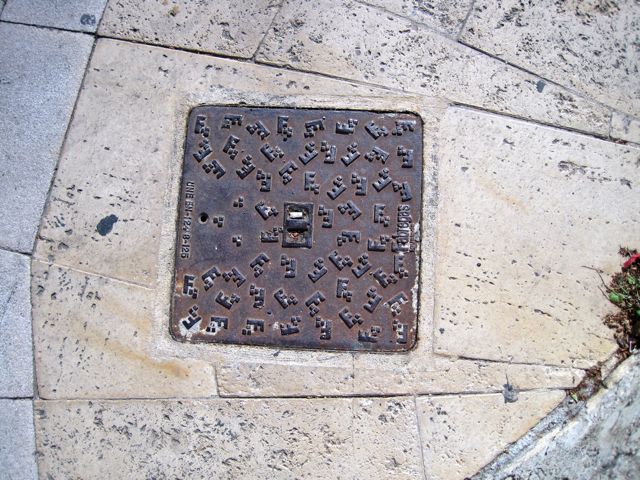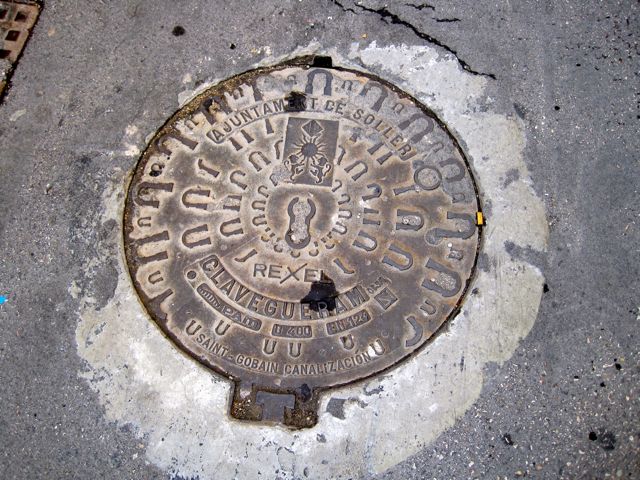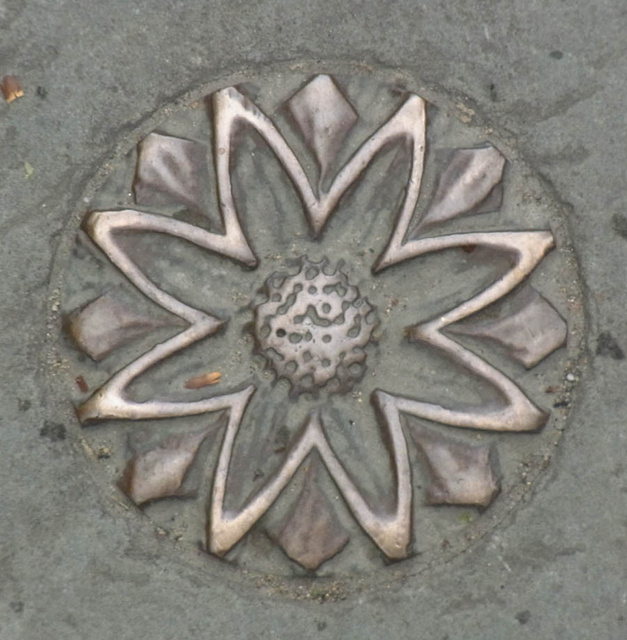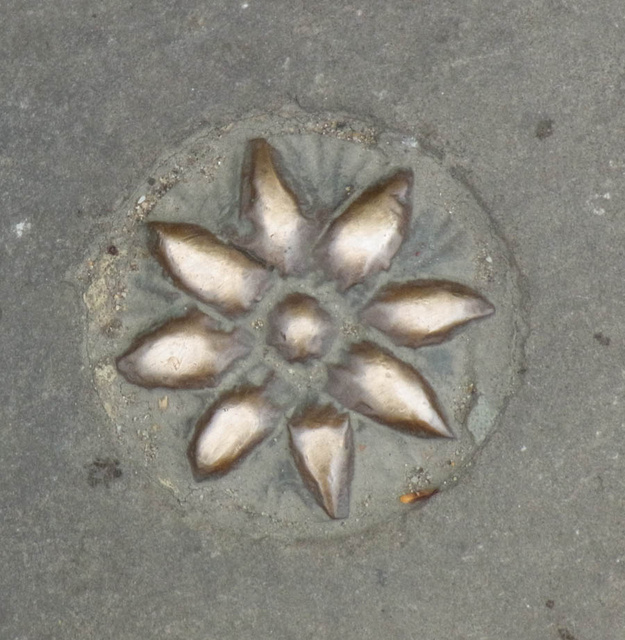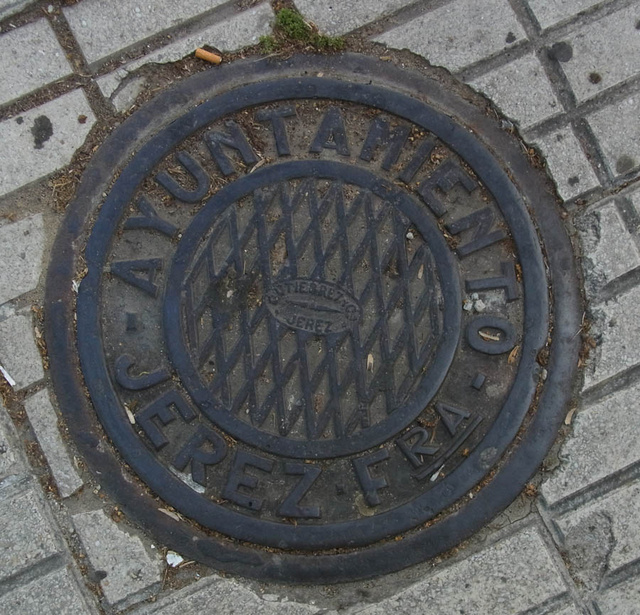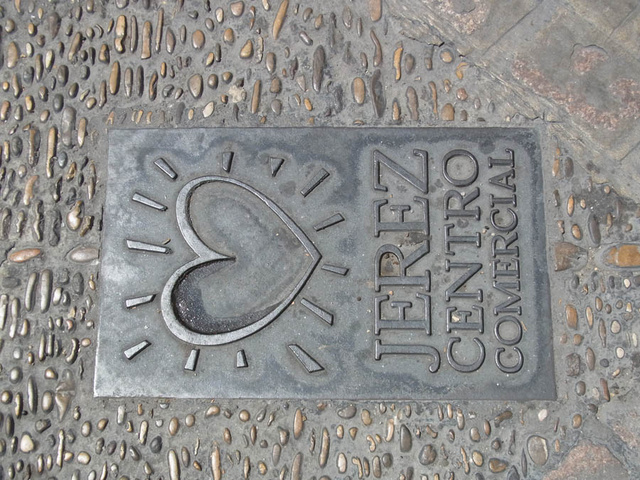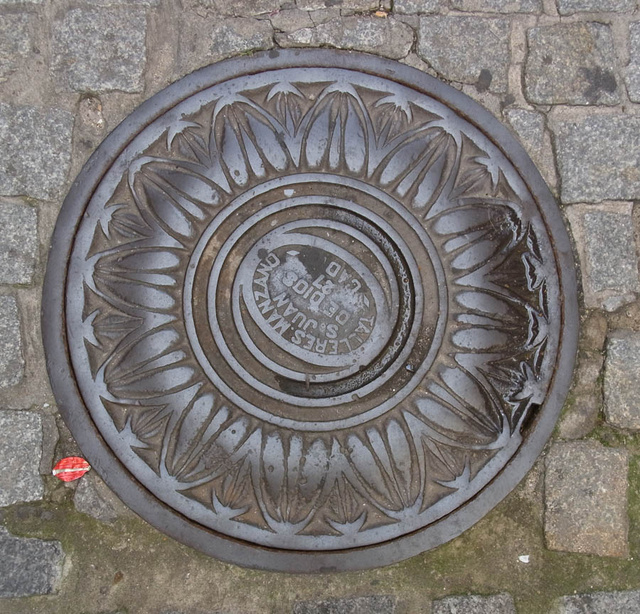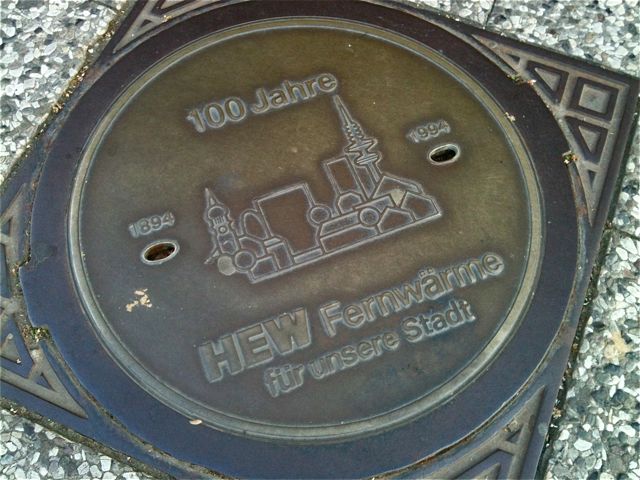
Sagt mal, kann irgendeiner der anwesenden Schriftkundigen diesen Buchstabensalat deuten?
Heißt das WYLK, YWLK, oder ist steckt da nicht sogar noch ein A drin? Das Teil liegt auf den Philippinen, wahrscheinlich in Manila und der Salat könnte auf eine Gießerei oder einen Wasser- oder Stromversorger deuten, vielleicht auch ein Telekommunikationsunternehmen — was sich halt alles so unter Schachtabdeckungen tummelt.
Ist es einfach Schrift?
Ganz ähnliche Zeichen:
Freund bertel vermutet, glaube ich, dass es sich um ein Schriftzeichen handelt. Ein handelsübliches sozusagen, woraus sich die erstaunliche Ähnlichkeit ergeben würde. Bliebe bloß die Frage, welches Land solche Zeichen schreibt oder früher schrieb. :-?
Freund bertel vermutet, glaube ich, dass es sich um ein Schriftzeichen handelt.
Auch bertel sieht eine Ligatur (oder ist das dann eher ein Monogramm? Jedenfalls abstrahierte Buchstaben übereinanderliegend) in seinem Beispiel, denn M A L und I sind doch erkennbar.
Nach einer oberflächlichen Suche behaupte ich dennoch, dass es sich bei der Deckelprägung um lateinische Zeichen handelt.
Keine echten manhole covers und daher vermutlich nur von untergeordneter Bedeutung, aber diese Ornamente findet man im Englischen Cambridge überall auf den Gehsteigen:
Hübsch! Ob das wohl reine Dekoration ist? Oder handelt es sich um schön gestaltete Messpunkte oder Markierungen?
Wohl kaum, dafür sind es viel zu viele die sich überall in der Stadt befinden. Ich glaube es handelt sich wirklich um Verzierungen.
Um wenigstens noch etwas Material nachzuliefern: hier sind zwei echte manhole covers sowie eine Verzierung vom Spanischen Jerez de la frontera. :-)
Eschwege:
Hamburg:
In der Nähe des hübschen Englischen Hafenstädtchens Mevagissey in Cornwall finden sich die »Verlorenen Gärten von Heligan«. Hier werden wunderschöne und soweit ich herausfinden konnte wohl zumindest zum Teil auch originale Eisengitter als manhole covers verwendet.
Wobei man sich ja schon fragen muss, wo man landet, wenn man in Venedig in einen Gulli steigt … :-o
Mal wieder ein paar iPhone-Details aus Chur, Graubünden, Schweiz.
Ich hatte ja auch noch einen Gullideckel angekündigt.
Ich habe hier noch was hauptstädtisches gefunden, direkt vorm Reichstag - mittlerweile machen mich meine Kinder auf so etwas aufmerksam.